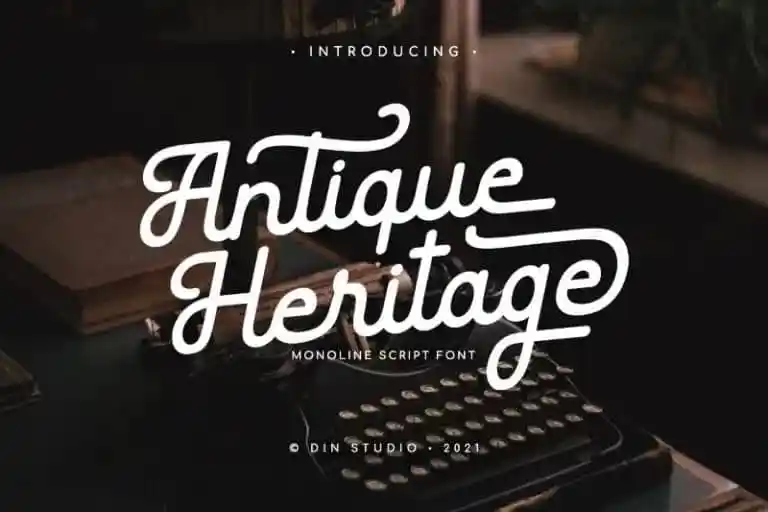
Antique Heritage Script Font – Fonte Grátis
Antique Heritage Script Font
A Antique Heritage Script Font é uma elegante tipografia monolínea que se destaca pela sua simplicidade e beleza, projetada pelo Din Studio para designers em busca de um revigorador na era moderna. Esta fonte idealmente complementa trabalhos antigos e vintage, dando-lhes um novo tom, enquanto promove uma sensação inigualável de tempo imóvel. Suas linhas simples e fluidas são perfeitas para aplicar a um design que exalte o encanto dos tempos passados. Seja no design de cabeçalos, logotipos, cartões de visita, citações impressas ou convites variados, cards, embalagens ou em seu próprio projeto de marca na web ou nas redes sociais – Antique Heritage Script Font trará um toque único e nostálgico que certamente deixará sua marca.